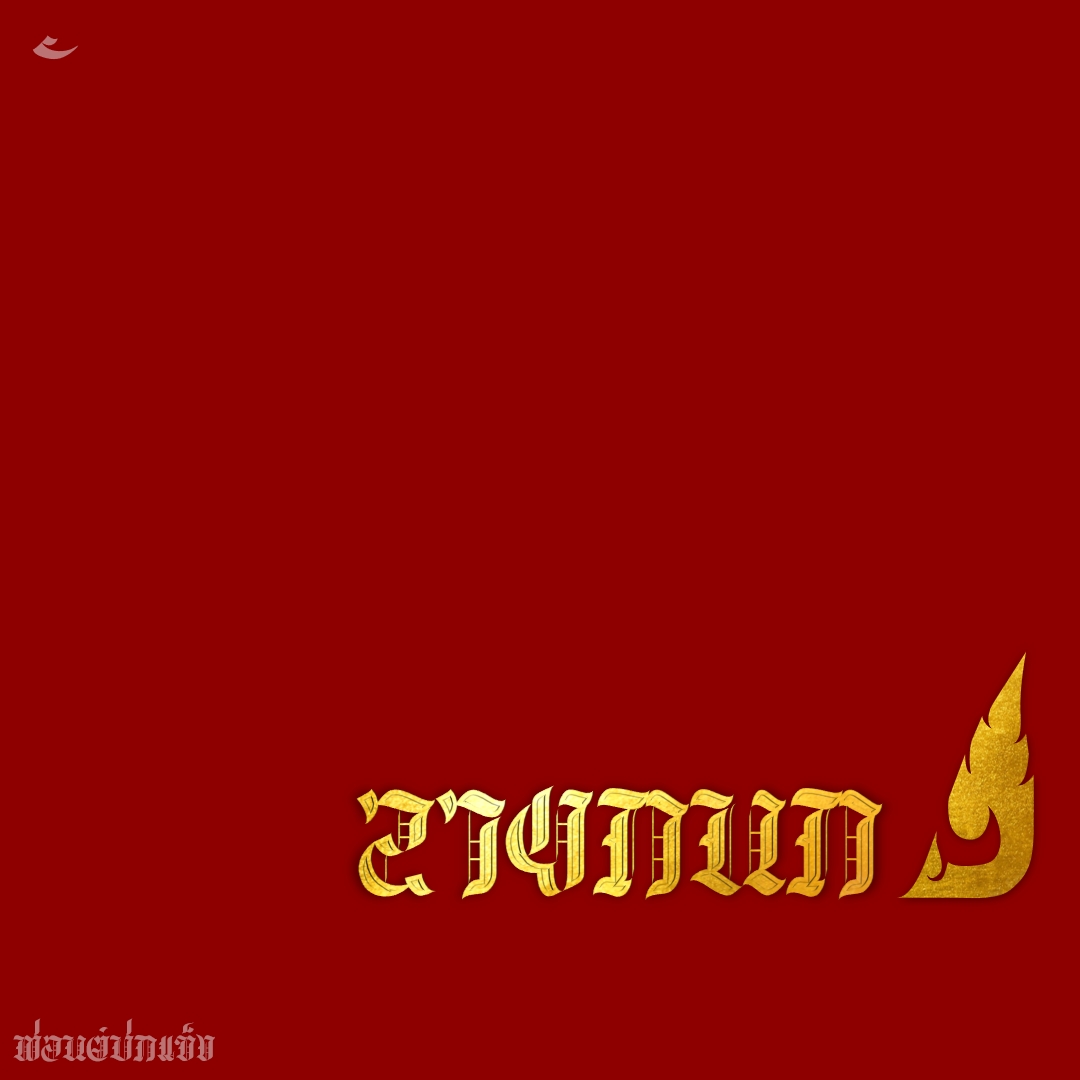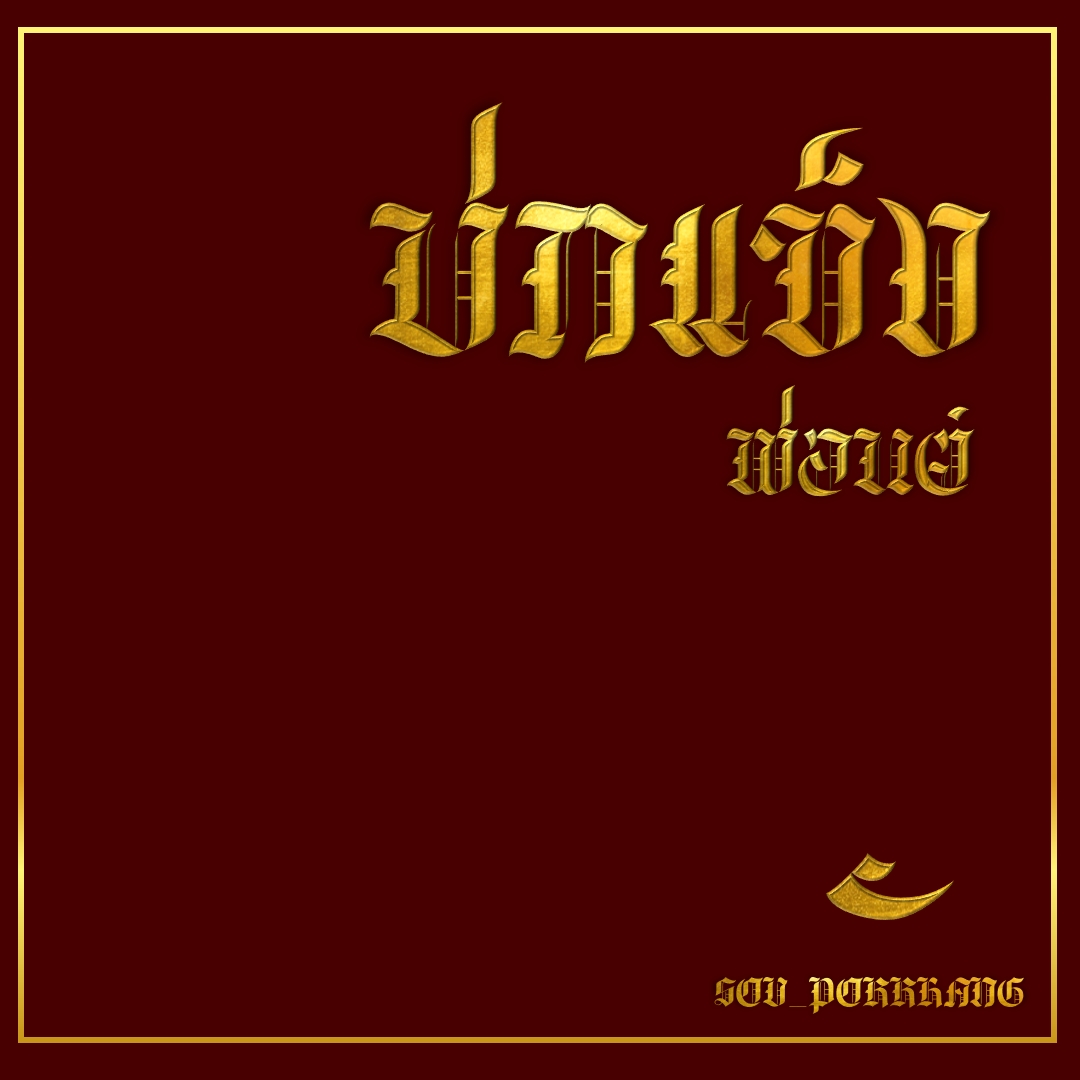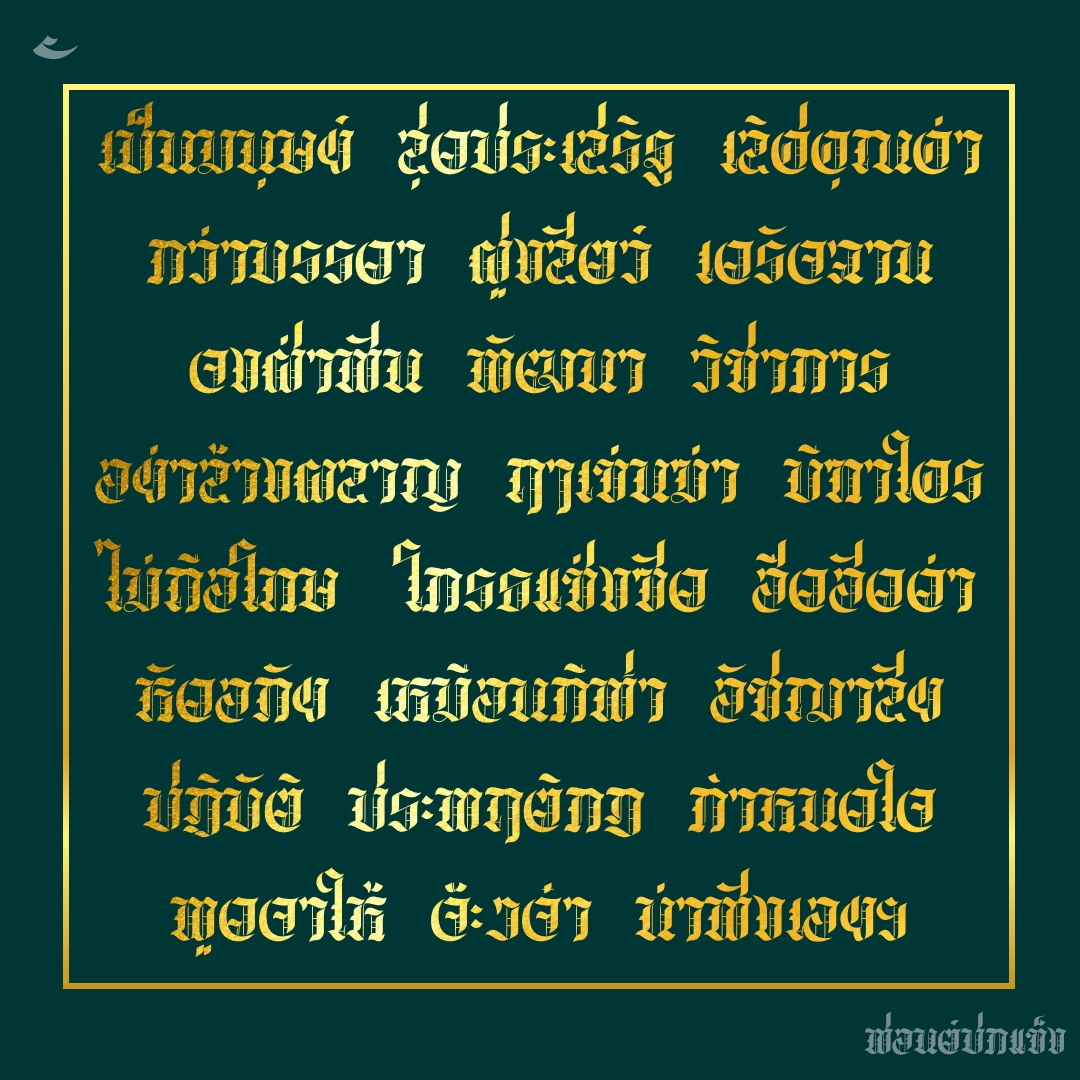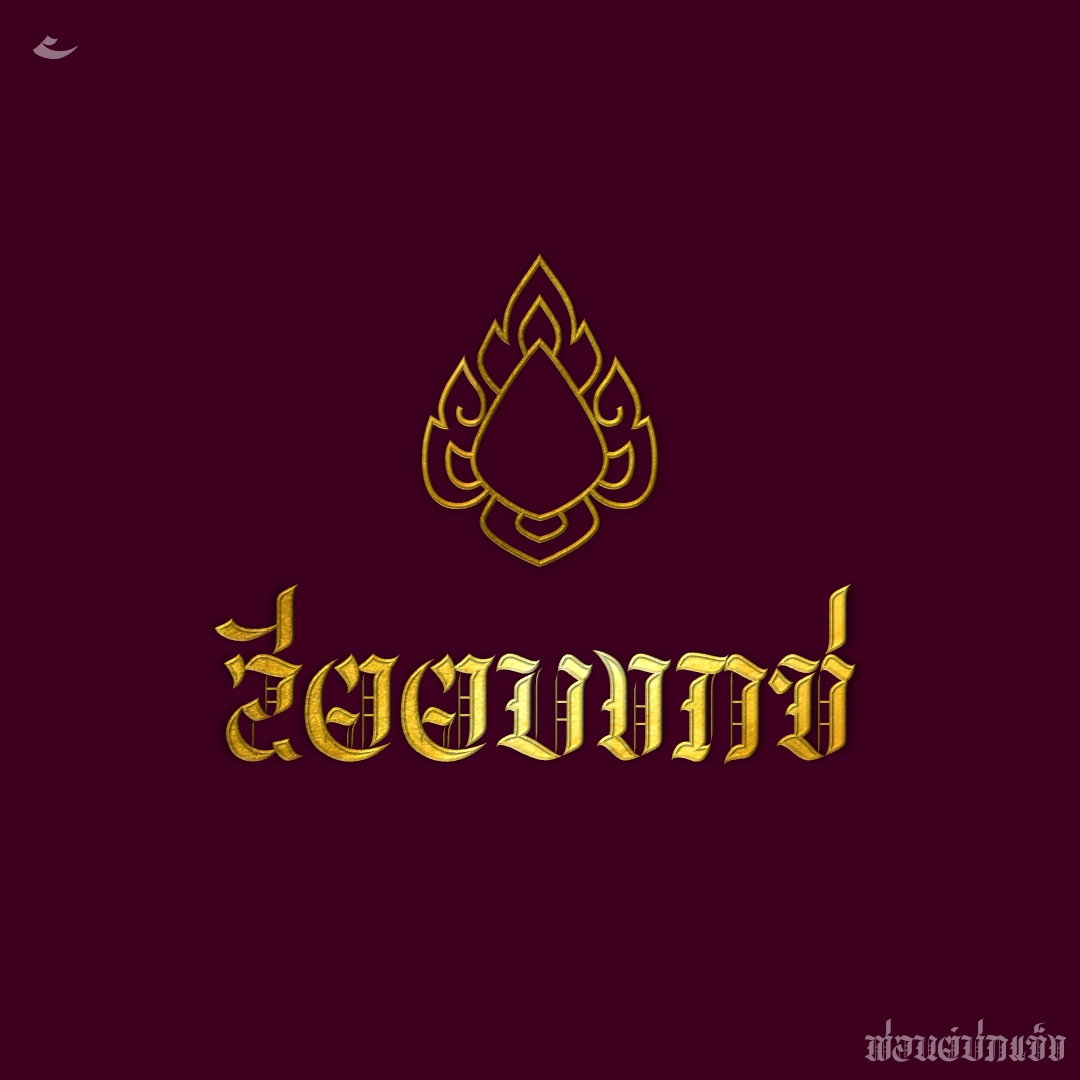
ฟอนต์ ปกแข็ง
ฟอนต์ปกแข็ง อักษรแนว gothic ที่ติดค้างไว้นานปี ทำเฉพาะ capital letters ตามแบบต้นฉบับที่เป็นปกหนังสือไทยสมัย 100 ปีก่อน เหมาะใช้เฉพาะคำสั้นๆ
ชื่อฟอนต์ : ปกแข็ง
ฟอนต์ปกแข็ง อักษรแนว gothic ที่ติดค้างไว้นานปี ทำเฉพาะ capital letters ตามแบบต้นฉบับที่เป็นปกหนังสือไทยสมัย 100 ปีก่อน เหมาะใช้เฉพาะคำสั้นๆ